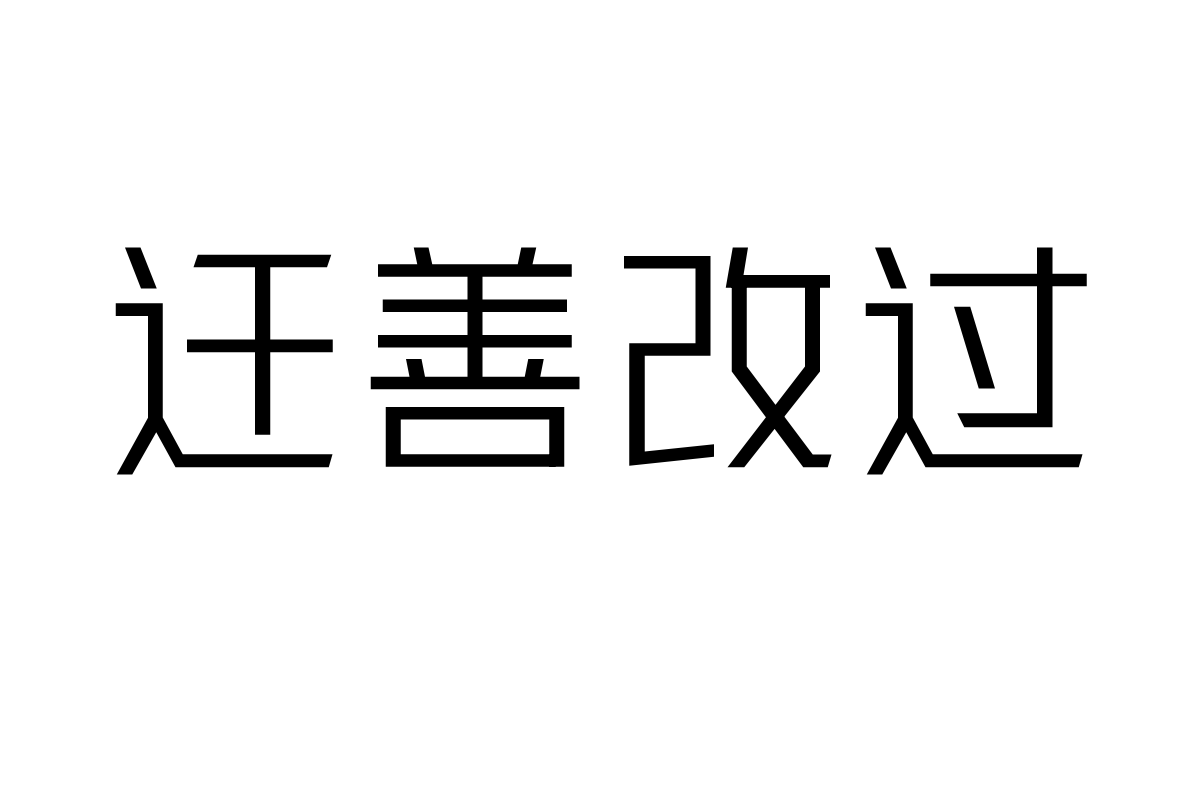
三极黑是一款具有独特风格的中文简体字体,由设计师精心打造。这款字体线条流畅,结构简洁,给人一种清新、自然的感觉。其笔画粗细适中,既有力度感又不失柔和,适合用于标题、正文等多种场合。同时,三极黑的字形设计也兼顾了美观和实用性,使得文字在视觉上更加协调,易于阅读。无论是用于印刷还是电子显示,三极黑都能展现出其独特的魅力。